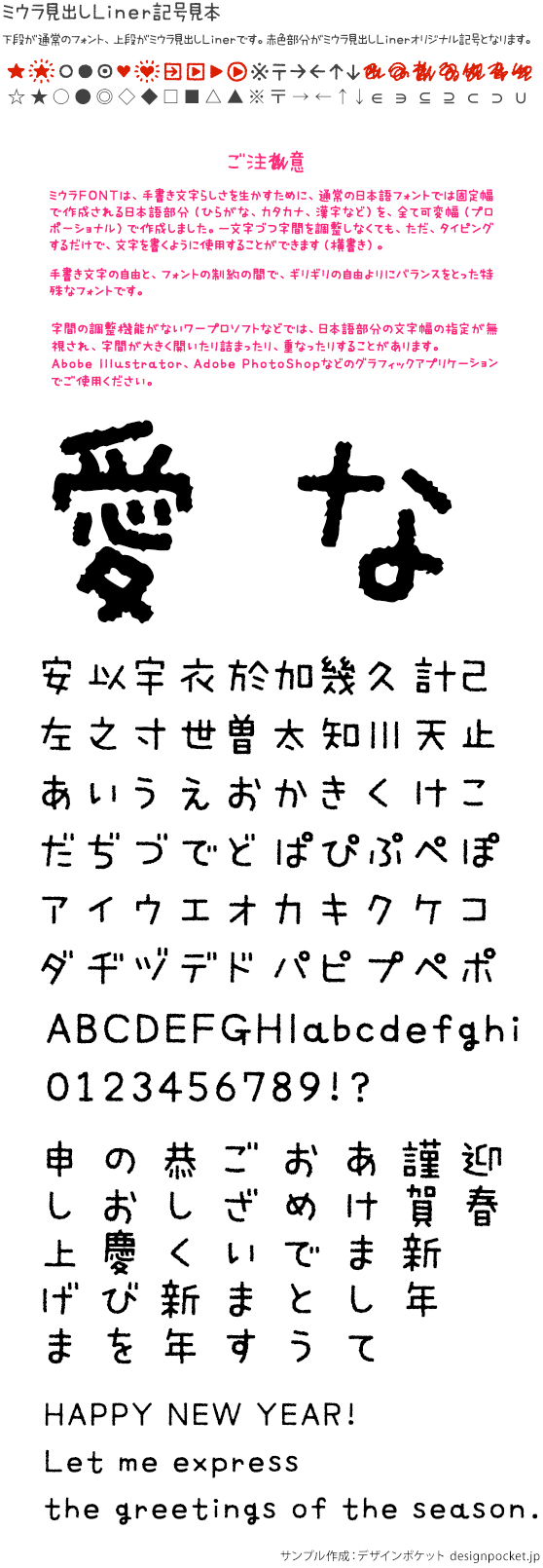
手書き風書体
ミウラ見出しLinerOtf R
手書き文字らしさを生かすために全ての文字を可変幅(プロポーショナル)で作成した特殊なフォント。「ぐちゃっ」とした書き直し筆跡など、オリジナルの記号も魅力です。
字面が小さく本文向きなミウラLinerもあります。
MopStudioの「ミウラFONT」シリーズは、可変幅と特殊文字が特徴の手書き風デザイン書体です。手書き文字らしさを最大限に表現するため、日本語書体としては異例にも全ての文字を可変幅 (プロポーショナル) で作成した特殊なフォント。「グシャっ」とした書き直し筆跡など、オリジナルの記号も魅力です。